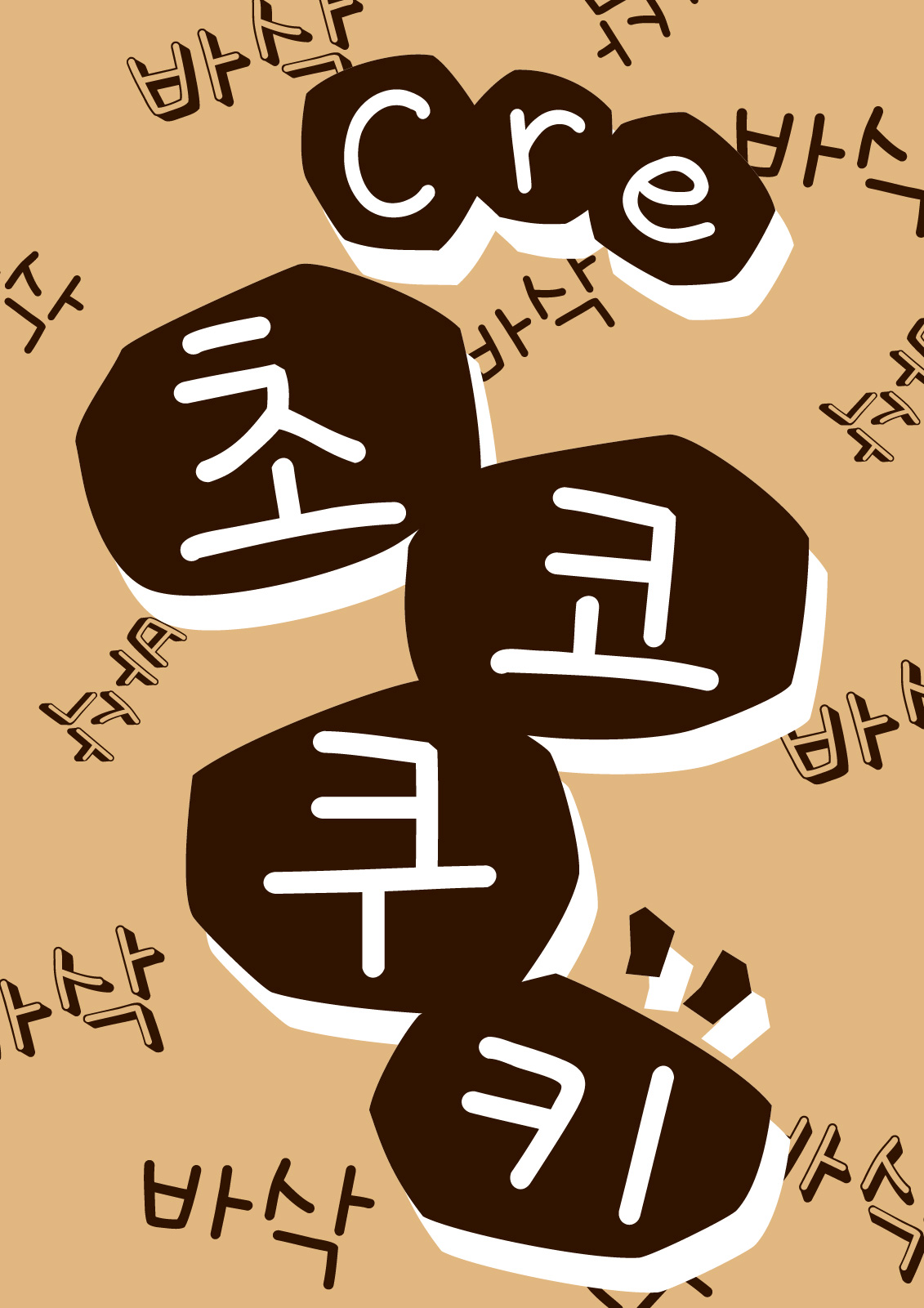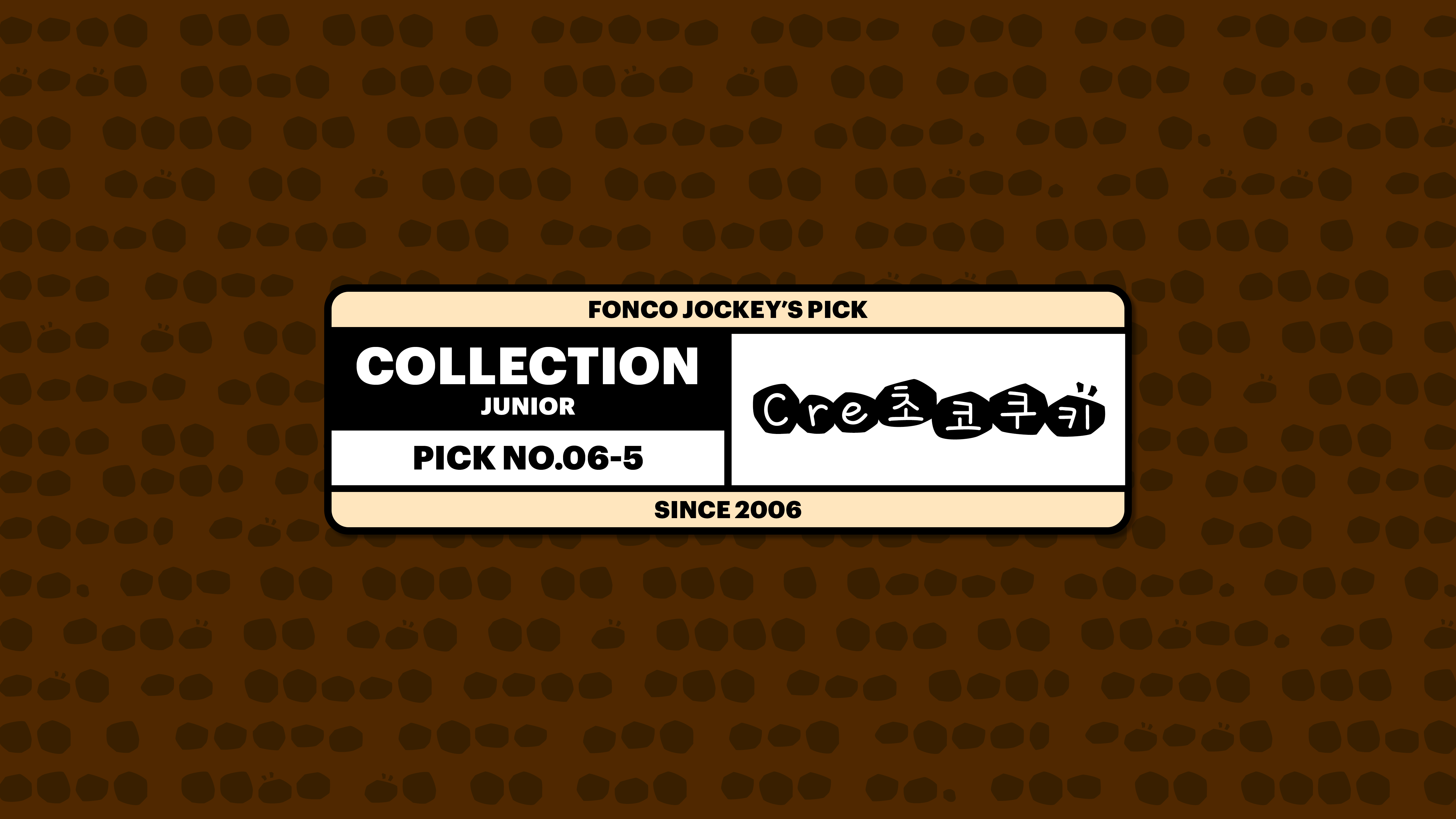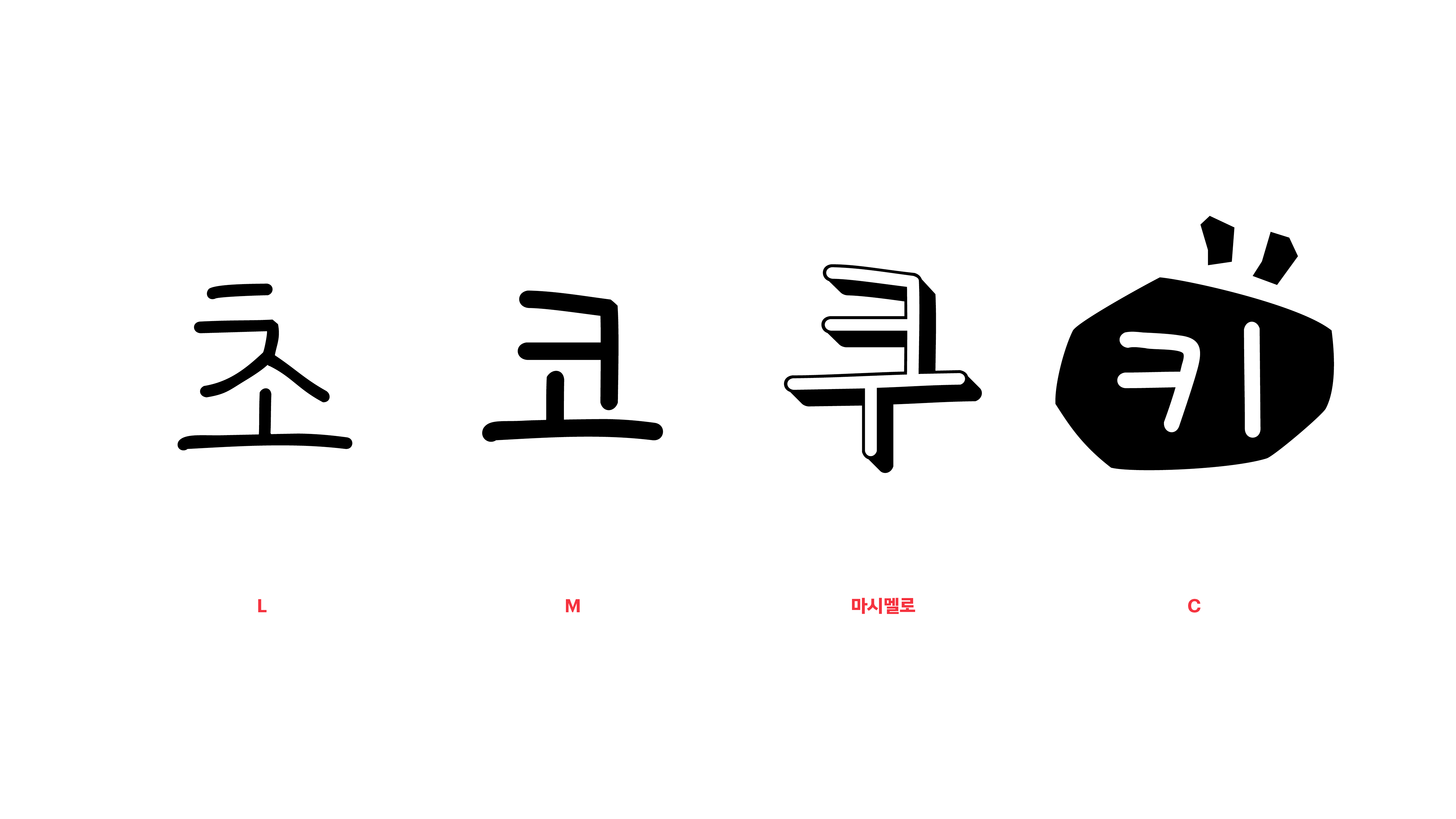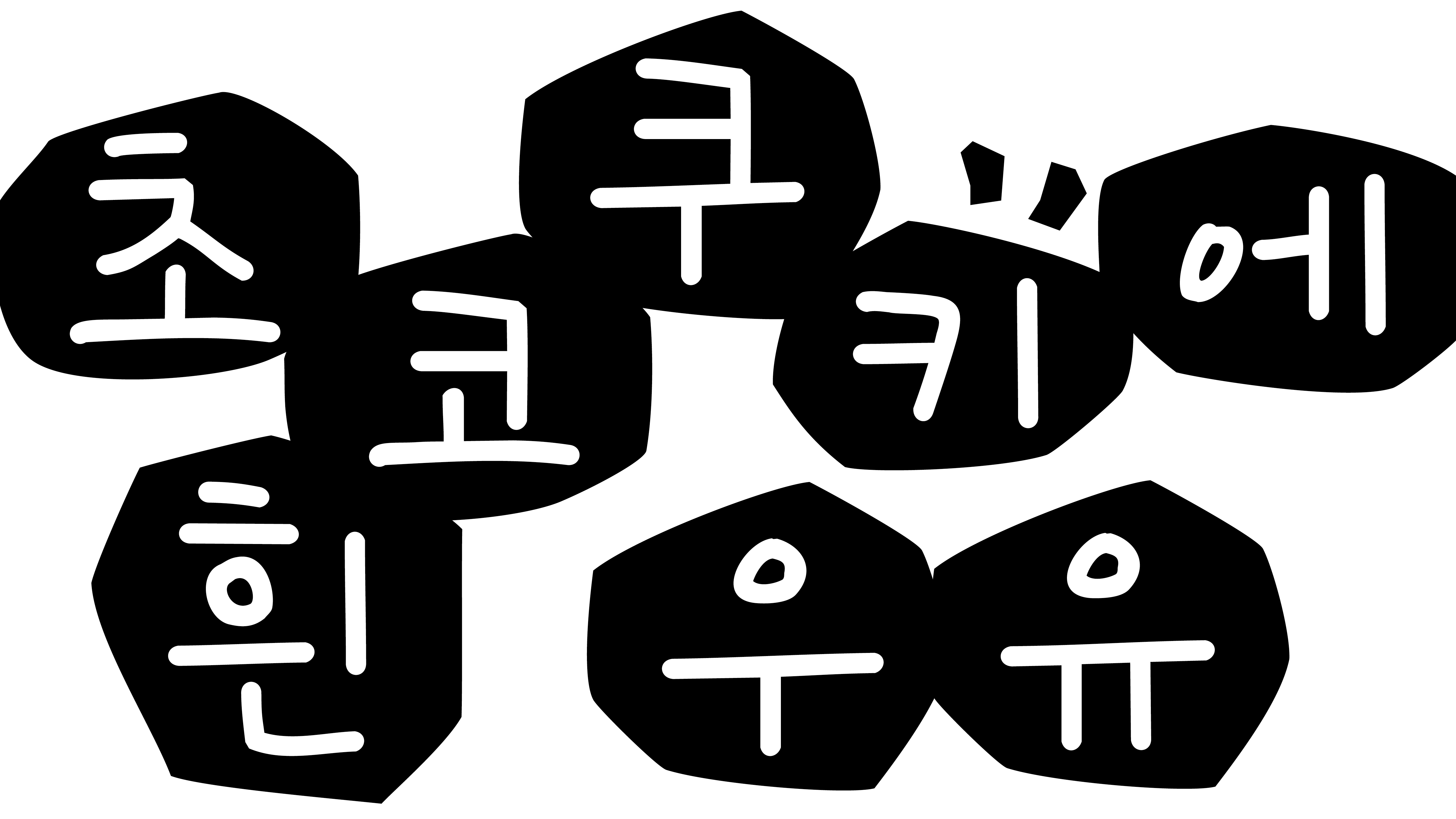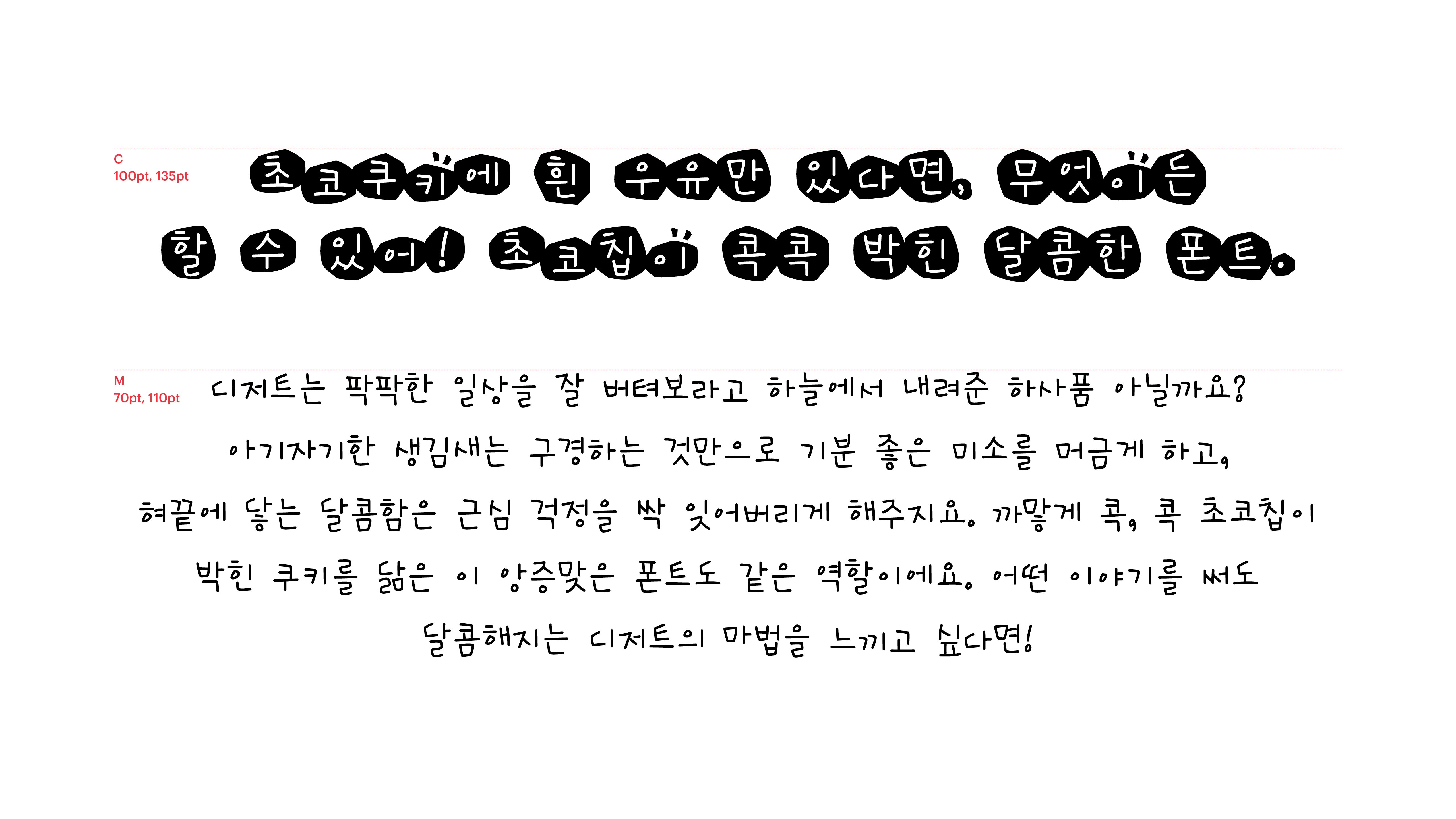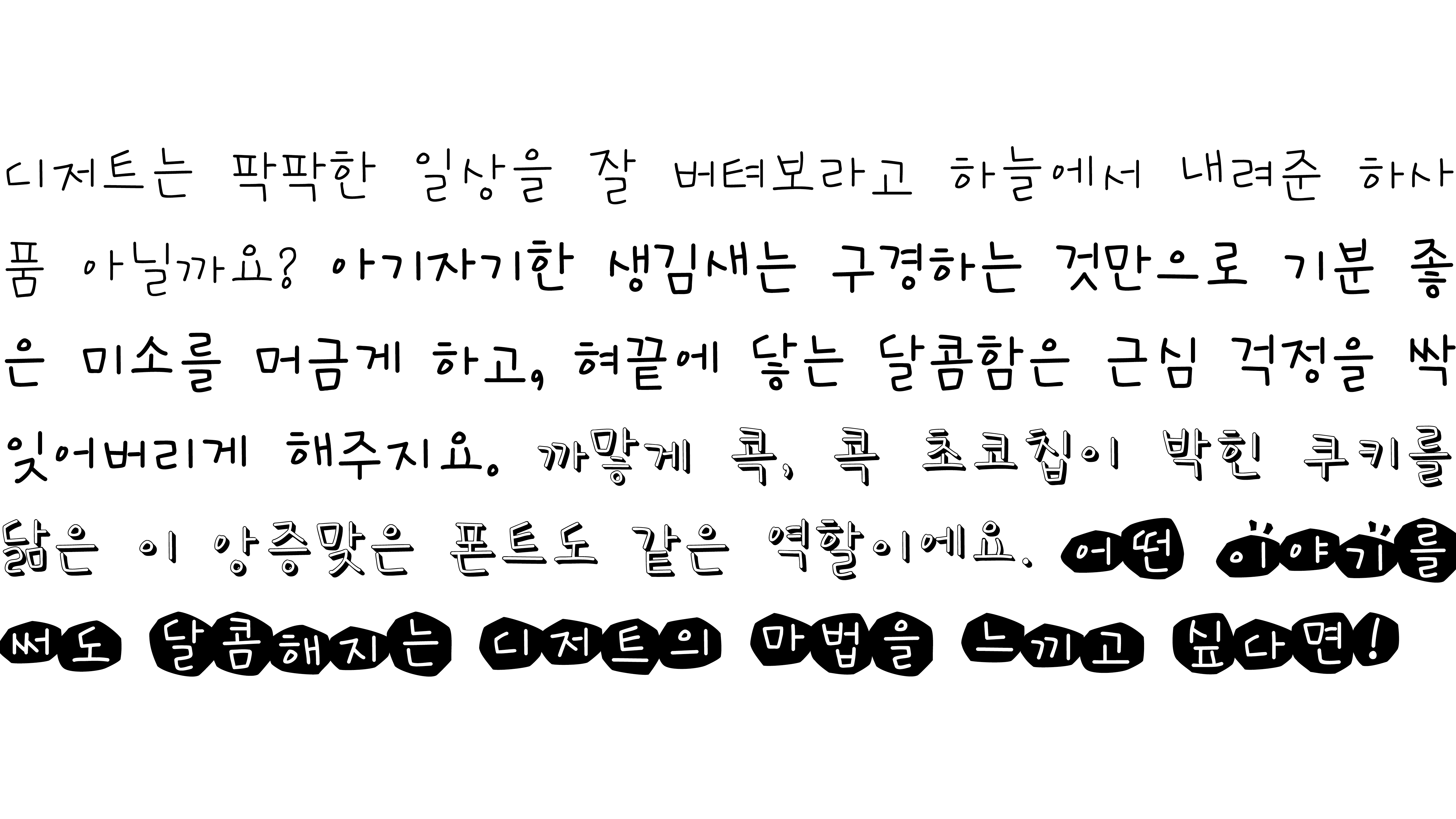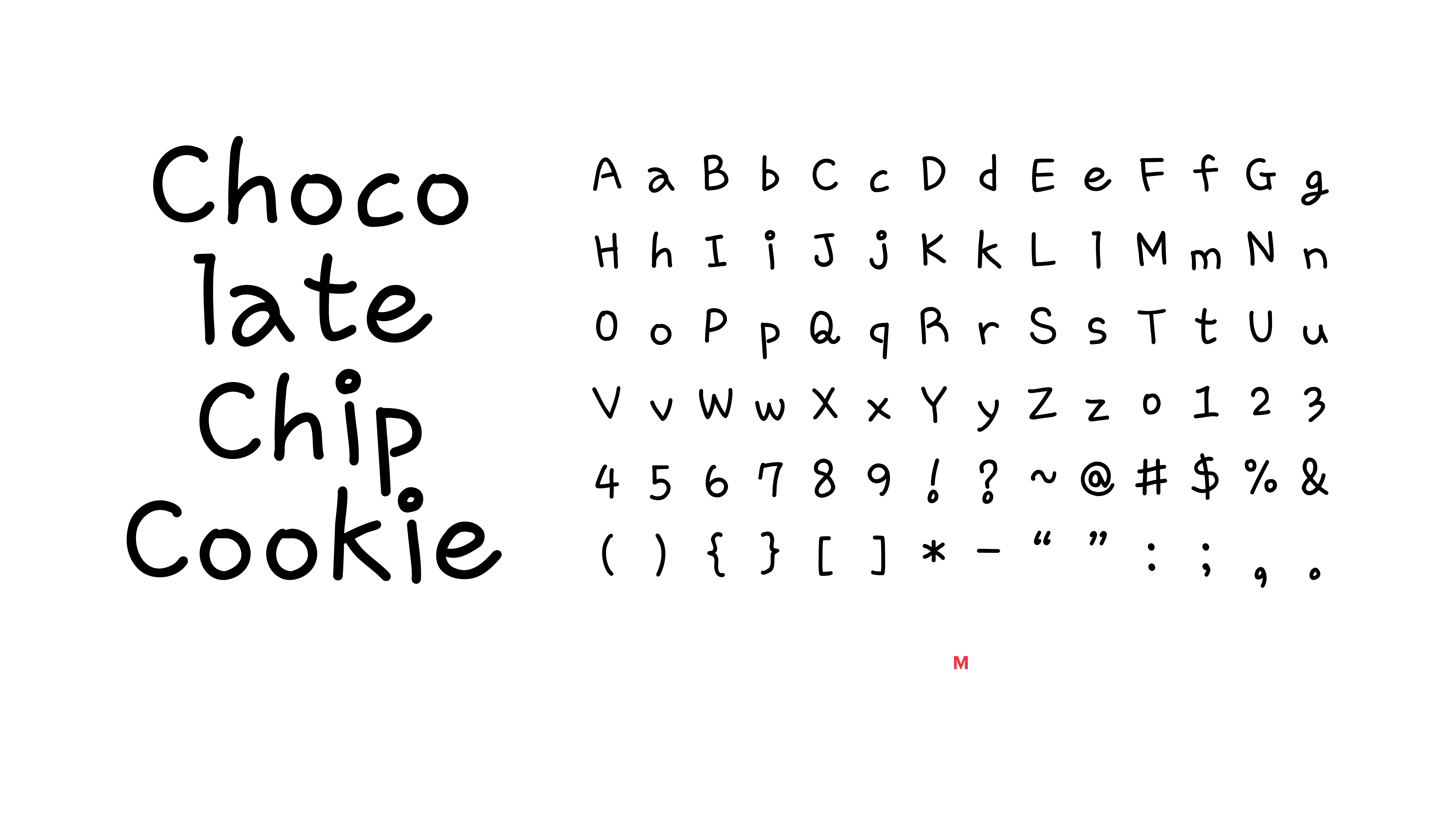
디저트는 팍팍한 일상을 잘 버텨보라고 하늘에서 내려준 하사품 아닐까요? 아기자기한 생김새는 구경하는 것만으로 기분 좋은 미소를 머금게 하고, 혀끝에 닿는 달콤함은 근심 걱정을 싹 잊어버리게 해주지요. 까맣게 콕, 콕 초코칩이 박힌 쿠키를 닮은 이 앙증맞은 폰트도 같은 역할이에요. 어떤 이야기를 써도 달콤해지는 디저트의 마법을 느끼고 싶다면!
Yoon Cre초코쿠키